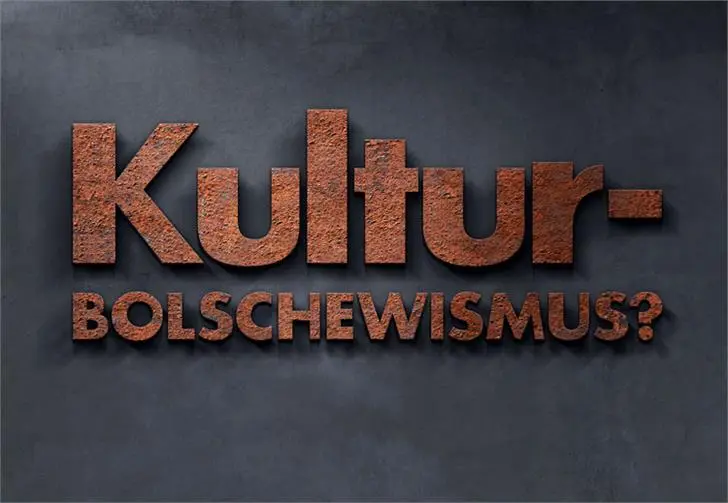
A fonte Kulturbolschewismus é uma escolha perfeita para quem busca uma tipografia sem serif que seja tanto moderna quanto forte. Criada pelo designer HENRIavecunK, esta sans-serif traz um equilíbrio entre elegância e força, adequando-se perfeitamente a qualquer projeto onde desejas transmitir clareza e simplicidade. O título inspirado na frase inquietante “Here we go again… “, remete à necessidade urgente de tomar atitudes em prol do futuro. Seu design agressivo mas bem balanceado, faz deste um recurso gráfico ideal para comunicar convicções firmes sem perder a sofisticação. A Kulturbolschewismus é uma excelente opção para qualquer projeto que busque expressar força e propósito no seu espaço digital.